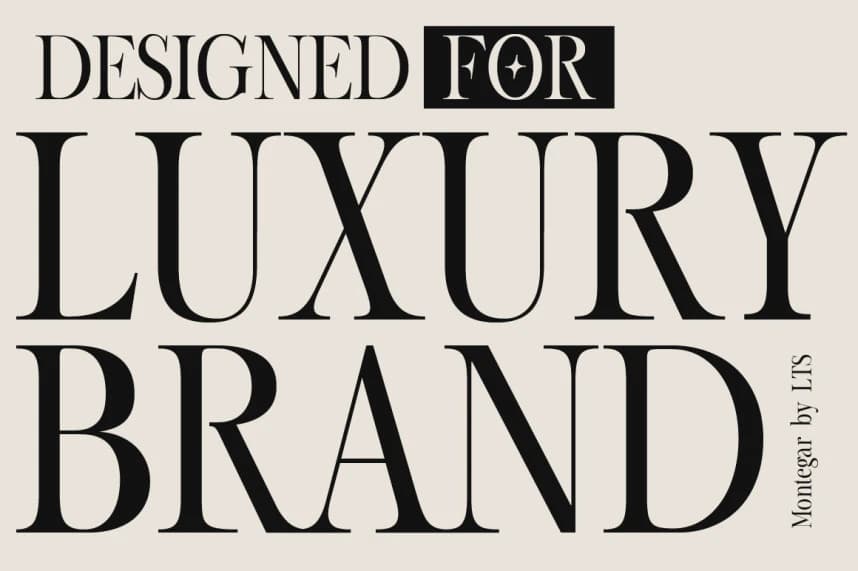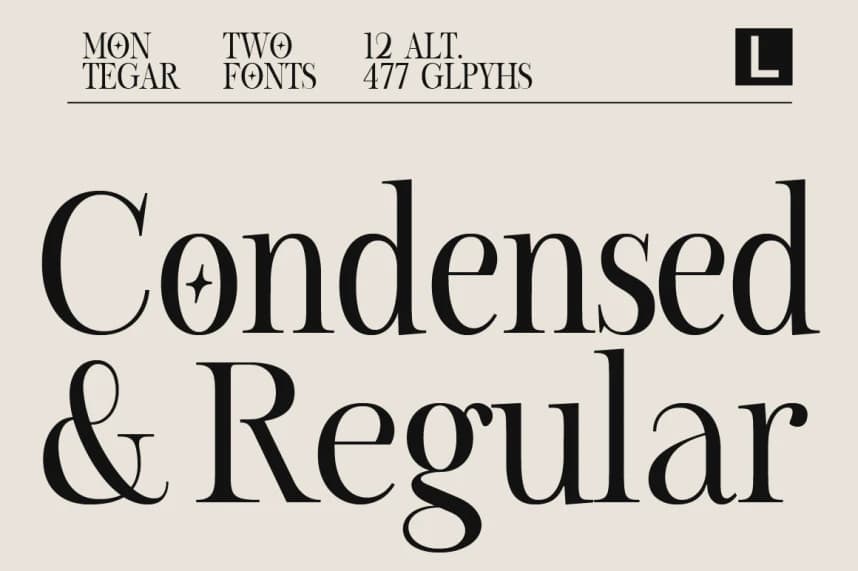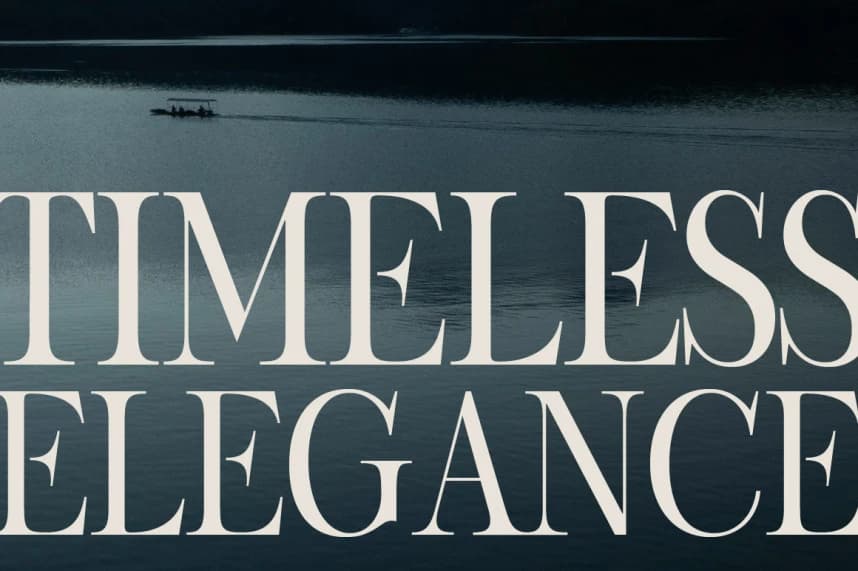
Montegar Font
Montegar Font, premium marka kimliği, editoryal başlıklar, moda kimlikleri ve sinematik tipografi için tasarlanmış modern bir lüks serif yazı tipidir. Zarif oranlara sahip, dramatik kontrast ve ince serif detaylarıyla zarif bir görünüm kazandırır.
Montegar Font, premium markalaşma, editoryal başlıklar, moda kimlikleri ve sinematik tipografi için tasarlanmış modern bir lüks serif yazı tipidir. Zarif oranlar, çarpıcı kontrast ve rafine serif ayrıntılarıyla tasarlanmıştır